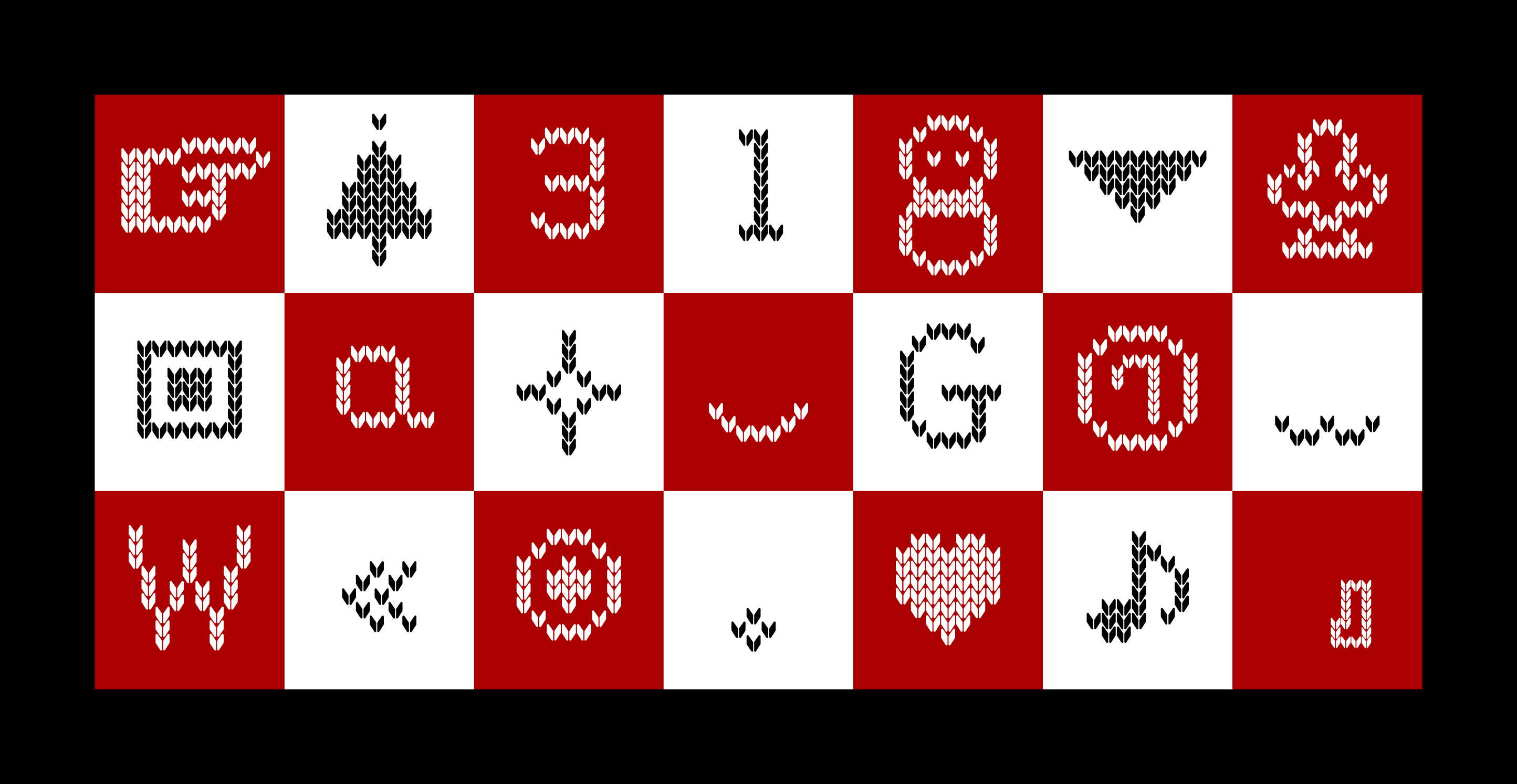
‘선물(Present)’은 언제나 잊지 않고 돌아와주는 겨울을 기다리는 마음을 담아 제작된, 따뜻하고 포근한 감성의 글꼴입니다. 각 픽셀 컴포넌트는 단순한 점이 아닌 니트의 짜임으로 구성되어 있으며, 이는 서툴러도 정성스럽게, 투박하더라도 애정을 담아 떠내려간 목도리를 떠올리게 합니다. 글자의 세로 인상과 자연스레 길어지는 단락은 마음을 덧댈수록 길어지는 목도리처럼 커져만 가는 사랑의 무게를 닮아 있습니다. 총 11,172자의 한글 글리프와 52자의 로마자, 182자의 기호 활자를 지원하며, 눈사람과 크리스마스트리 등 ‘선물(Present)’만의 특별한 기호 활자들이 곳곳에 숨겨져 있습니다. 정성과 애정을 꾹꾹 눌러 담아 전하고 싶은 마음이 있다면 ‘선물(Present)’을 통해 그 진심을 건네보세요.
선물체
Present
‘선물(Present)’은 언제나 잊지 않고 돌아와주는 겨울을 기다리는 마음을 담아 제작된, 따뜻하고 포근한 감성의 글꼴입니다. 각 픽셀 컴포넌트는 단순한 점이 아닌 니트의 짜임으로 구성되어 있으며, 이는 서툴러도 정성스럽게, 투박하더라도 애정을 담아 떠내려간 목도리를 떠올리게 합니다. 글자의 세로 인상과 자연스레 길어지는 단락은 마음을 덧댈수록 길어지는 목도리처럼 커져만 가는 사랑의 무게를 닮아 있습니다. 총 11,172자의 한글 글리프와 52자의 로마자, 182자의 기호 활자를 지원하며, 눈사람과 크리스마스트리 등 ‘선물(Present)’만의 특별한 기호 활자들이 곳곳에 숨겨져 있습니다. 정성과 애정을 꾹꾹 눌러 담아 전하고 싶은 마음이 있다면 ‘선물(Present)’을 통해 그 진심을 건네보세요.
‘Present’ is a warm and gentle display typeface, created with the quiet hope that winter—like a promise softly remembered—will return once more. Each pixel component is formed not as a simple dot, but as a knitted stitch—Clumsy hands, but love in each stitch, Rough edges, but heart in every pitch. The elongated vertical form of the letters and the naturally lengthening paragraphs resemble a scarf growing longer with each added thought, echoing the ever-growing weight of love. Supporting 11,172 Hangul glyphs, 52 Latin characters, and 182 symbols, some with hidden touches of joy (such as snowmen and Christmas tree). If there’s something you wish to give with care, let ‘Present’ be the way your heart is told.